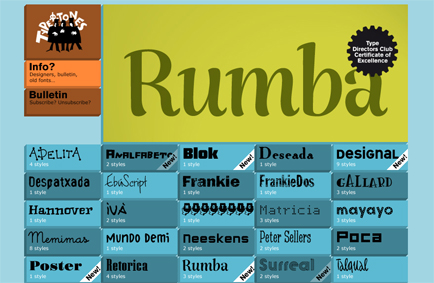
Quizas por el periodo en el que cada componente del colectivo tipográfico Type-Ø-Tones se dedicó a sus proyectos personales, a algunos les pudo dar la sensación de que el proyecto estaba en vía muerta… ni mucho menos. Type-Ø-Tones vuelven a primera línea con un nuevo diseño de su site y con renovadas energías para seguir compartiendo con su legión de seguidores esas tipografías, vibrantes, divertidas y llenas de vidas a las que nos tienen acostumbrados. No les damos la bienvenida… por que nunca se habían ido !!